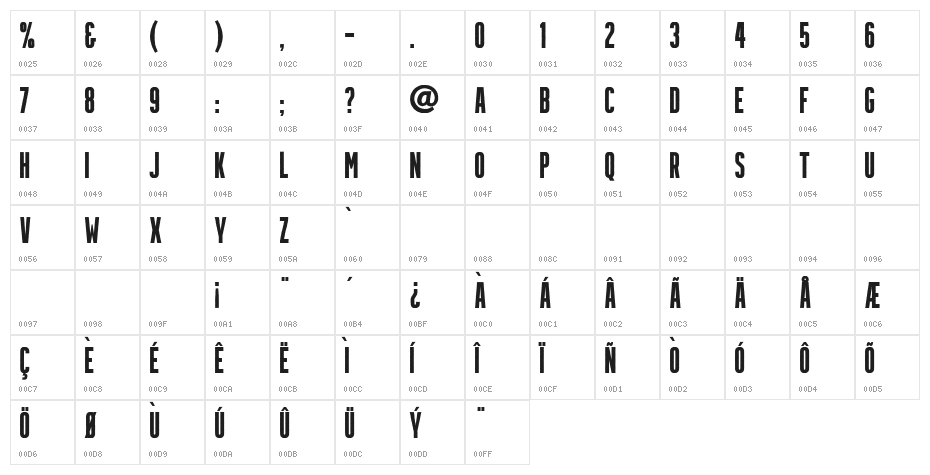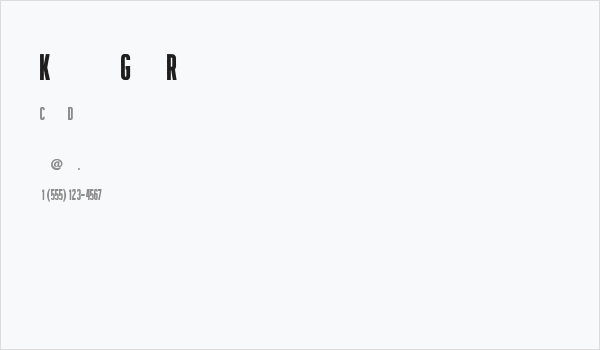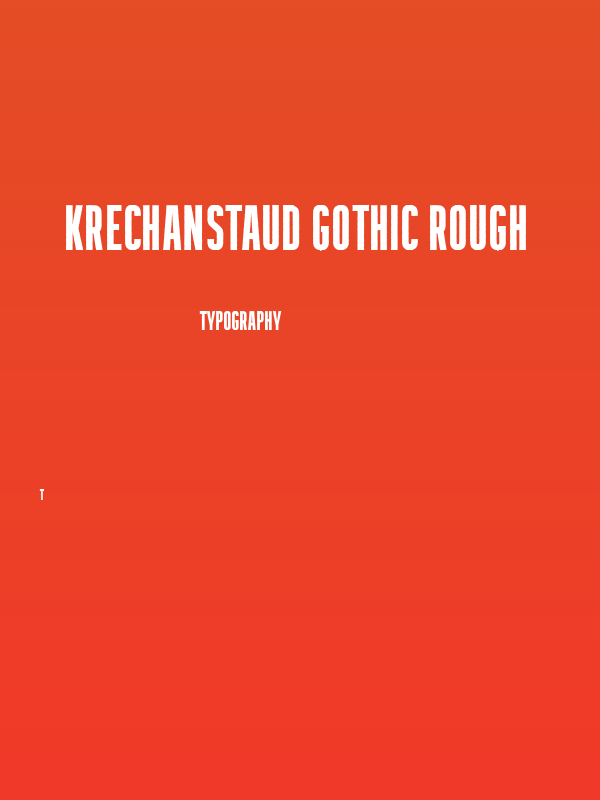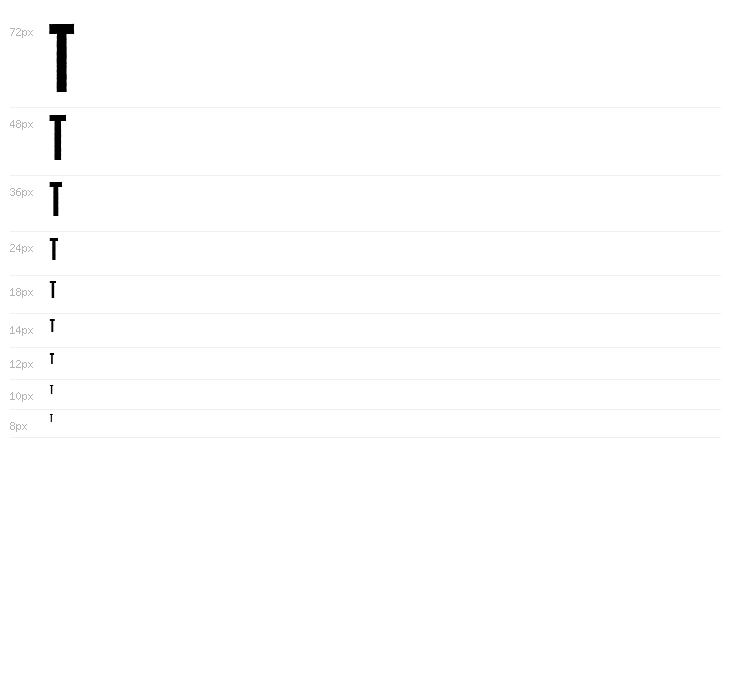
Krechanstaud Gothic Rough Font
✎ Distorted Eroded
| Gesamtstil | Vintage, Industrial |
| Vorgeschlagene Projekte | Ideal for posters, logos, branding, and any design needing a strong, vintage industrial aesthetic. |